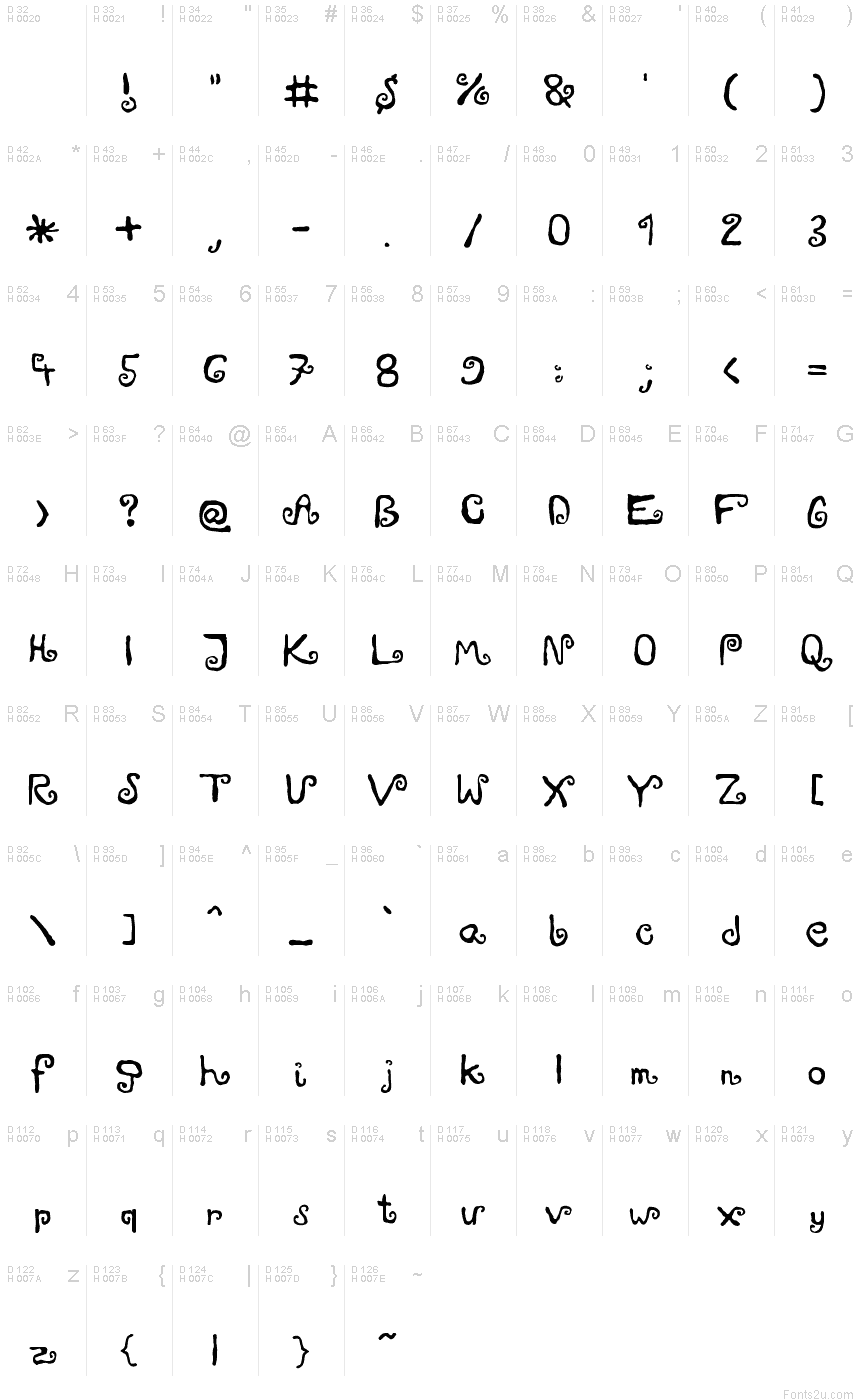
خط Zawijasy من wopi.art.pl هو خط عرض مجاني ومميز بلفات انسيابية تبدو وكأنها مرسومة بشرائط حبر سميكة. كل حرف يلتف في حلقات مرحة وأشكال ناعمة، مما يضفي على النص طابعاً مرسوماً يدوياً ومبهجاً يشبه الحلوى. إيقاع الخط حر وحيوي، لتبدو الكلمات وكأنها تتراقص على السطر بدلاً من أن تصطف بشكل جامد.
باستخدام Zawijasy، ستكتسب عناوينك فوراً طابعاً خفيفاً ومشاكساً بعض الشيء، وهو ما يجعله مثالياً لملصقات الأطفال، ودعوات أعياد الميلاد، وتغليف الحلوى أو الألعاب، والشعارات المرحة، ولافتات الحفلات، والرسومات الجريئة على وسائل التواصل الاجتماعي. يتألق هذا الخط المجاني عند استخدامه بأحجام كبيرة حيث تبرز كل تلك الالتفافات، ويفضل تنسيقه مع خط بلا زوائد (Sans Serif) بسيط ونظيف للنصوص الأساسية لضمان سهولة القراءة.